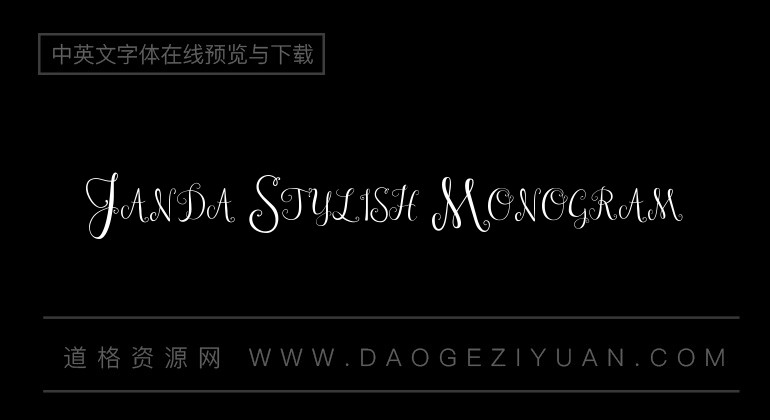
Janda Stylish Monogram
Janda Stylish Monogram 是一种优雅、精致的花体字体,由 Kimberly Geswein 设计。这个字体的特点是字母之间有很多曲线和花朵,看起来非常漂亮。它适合用于印刷品、婚礼邀请函、包装设计等需要高雅、精致风格的设计中。Janda Stylish Monogram 字体的每个字母都是一个单独的形状,这意味着您可以自由地组合字母来创造独特的标志或设计。
Janda Stylish Monogram是一款非常不错的手写艺术字体,具有很好的视觉感,适合于文化类的宣传设计、商业类品牌的广告和产品包装设计以及个性化文字排版等较多场景。